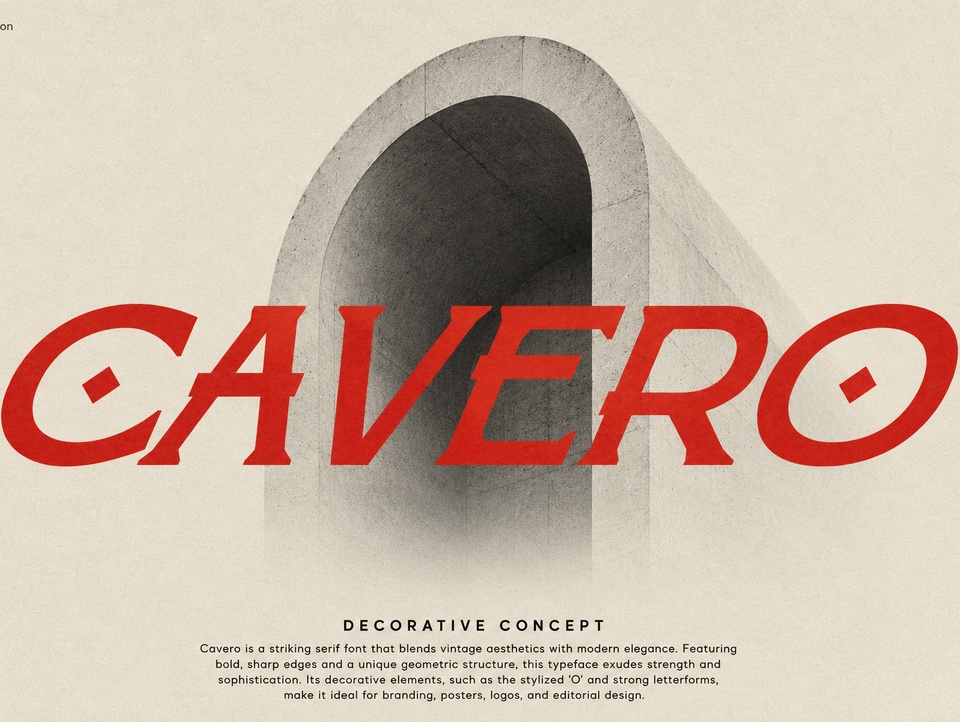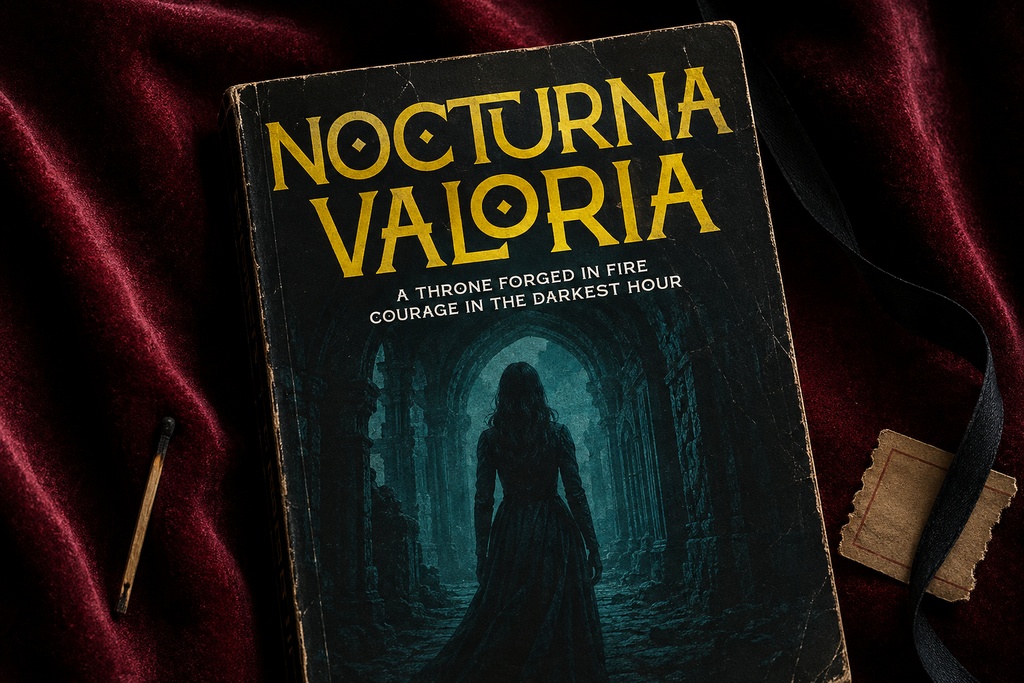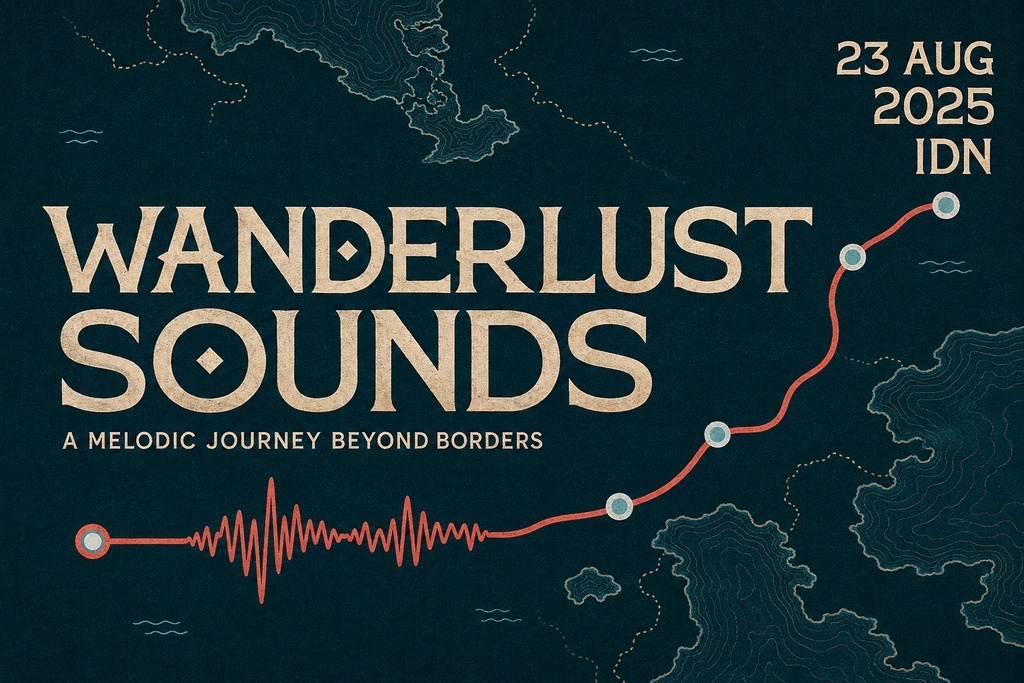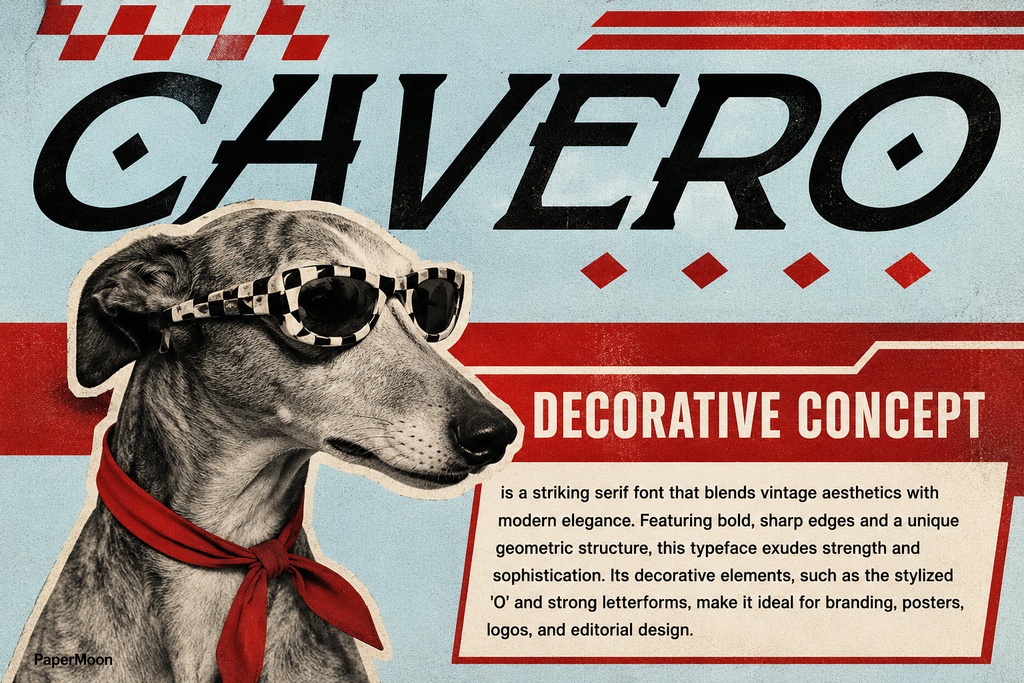
Cavero — ラグジュアリーなブランディングに最適な、コントラストの強い装飾的セリフフォント
Caveroは、力強い幾何学的な構成と芸術的なエレガンスを融合させた、印象的な装飾セリフフォントです。シャープなエッジ、個性的な字形、そしてコントラストの高いセリフ構造によって、洗練されながらも大胆な印象を与えます。全体として、レトロとモダンが融合したCaveroの書体は、ヴィンテージの魅力と現代的なファッション性の間に位置する独特のキャラクターを備えています。 高いインパクトを求められるタイポグラフィのためのディスプレイセリフフォントとしてデザインされたCaveroは、ハイエンドなブランディング、エディトリアルデザイン、ポスター、ロゴなどに最適です。また、ラグジュアリーなパッケージデザインやプレミアムプロダクトのストーリーテリングにも自然に調和します。独自の個性を持つ大胆なディスプレイセリフとして、どのようなデザインにおいても細部までこだわった表現を引き立てます。 Caveroには、Cavero RegularとCavero Italicの2つのスタイルが収録されており、OTF、TTF、WOFF、WOFF2の4形式で提供されます。これにより、デスクトップパブリッシング、印刷、ライセンス取得済みのWebフォント利用まで、1つのパッケージで幅広く対応できます。PCとMacの両方で簡単にインストールできます。 Regularスタイルは、見出しなどで存在感を発揮する自信に満ちたステートメントフォントです。一方、Italicスタイルは、引用文、キャプション、アクセントラインなどに表情豊かな動きを加えます。両スタイルは同一の完全な文字セットを共有しているため、1つのレイアウト内で組み合わせても、自然で統一感のあるデザインを実現できます。 ## 主な特徴 Caveroの中心的な特徴のひとつが、充実したリガチャ(合字)機能です。標準リガチャと任意リガチャを含む豊富なリガチャセットにより、大きなディスプレイサイズでも文字同士が自然につながり、美しい文字組みを実現します。 さらに、Access All Alternatesに対応しているため、デザインソフトを離れることなく、細部まで丁寧に作り込まれた代替字形へ簡単にアクセスできます。特徴的な「O」やクリエイティブな字形によって、ワードマークにオーダーメイドのような個性的な仕上がりを加えることができます。 ファミリーには、分数、序数、上付き文字なども収録されており、エディトリアルデザインに求められる繊細な表現にも対応しています。最新のOpenTypeフォントとして設計され、対応アプリケーションで安定した文字間調整を実現する、最適化されたGPOSカーニングも搭載されています。 各スタイルには、完全な大文字・小文字、数字、豊富な句読点・記号が収録されています。また、幅広いヨーロッパ言語に対応する多言語アクセント文字もサポートしています。 Caveroは、Adobe Photoshop、Illustrator、InDesign、Figma、Canva、Affinity、Procreateなど、主要なデザインソフトウェアに対応しています。さらにWebにも対応しており、最適化されたWOFF2 Webフォントファイルによって、Webページの高速な読み込みをサポートします。 ## 用途 Caveroは、ランウェイキャンペーンやルックブックに使用するファッション・エディトリアルフォントとして活躍します。また、雑誌の特集ページや表紙に適したモダンなマガジンフォントとしても優れています。 イベント、コンサート、展示会などでは、視線を集める印象的なポスターフォントとして使用できます。 ブランドアイデンティティやロゴシステムには信頼性の高いブランディングフォントとして、プレミアムなブティック商品にはラグジュアリーなパッケージフォントとして適しています。また、ワードマークやモノグラムには、洗練されたロゴフォントとして使用できます。 このエレガントなエディトリアルセリフフォントは、見出し、引用文、メインビジュアルのテキストなどにも美しく映えます。インパクトのあるレイアウト、クリエイティブな構成、ブランドを象徴するステートメントデザインなど、力強く表現力豊かな字形を必要とするあらゆるデザインに適しています。 ## ライセンス Caveroは、デフォルトで商用ライセンスのフォントとして提供されます。推奨されるCubebrush Commercial Licenseでは、クレジット表記なしで、クライアント向けの完成作品や販売可能なアートワークなど、商用目的で使用できます。 Basic Licenseは、個人利用および非商用プロジェクトに限定されます。 フォントファイルそのものを単独の商品として再販売、共有、または再配布することは禁止されています。 今すぐCaveroをあなたのデザインツールキットに加えて、次のラグジュアリーブランド、ファッションプロジェクト、エディトリアルレイアウトに、力強さと洗練を兼ね備えた個性的なセリフ書体をプラスしましょう。